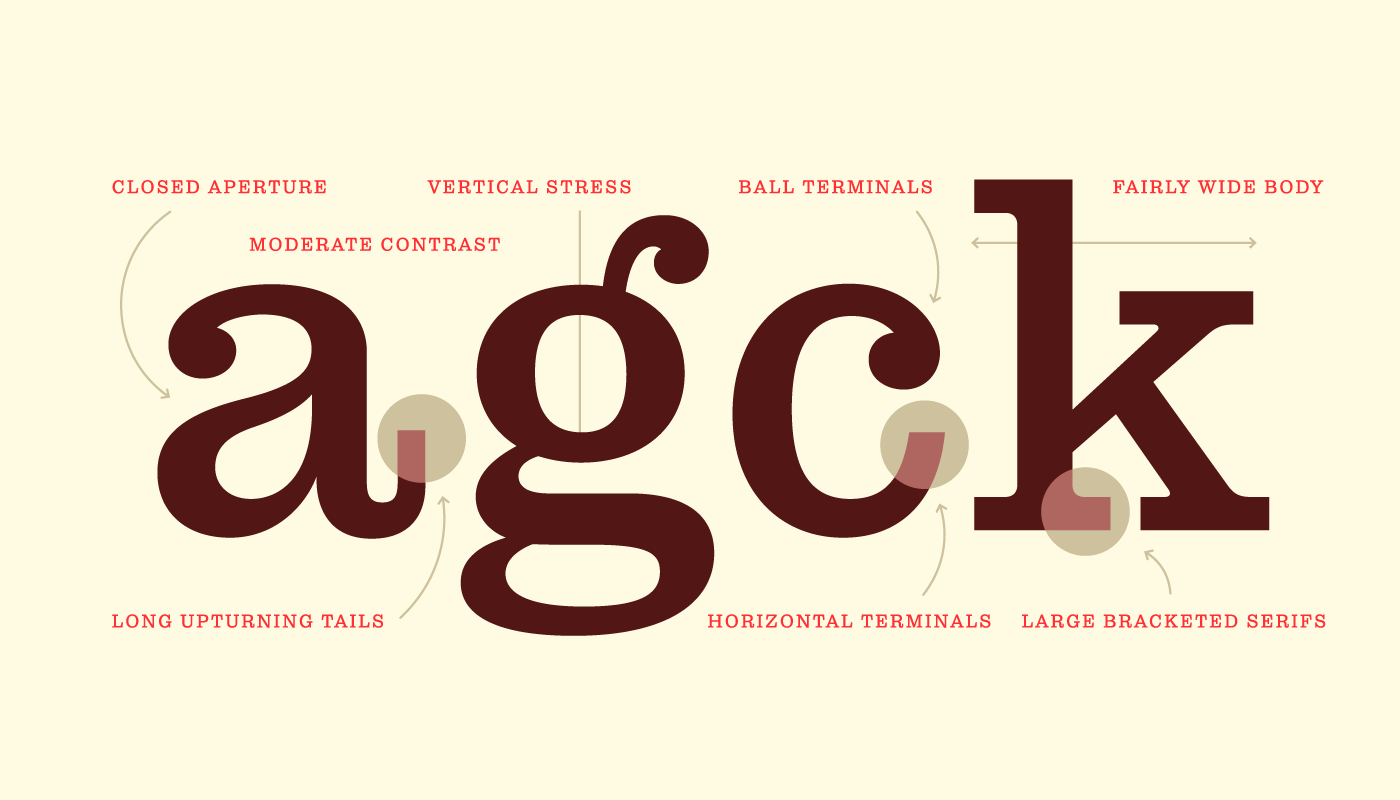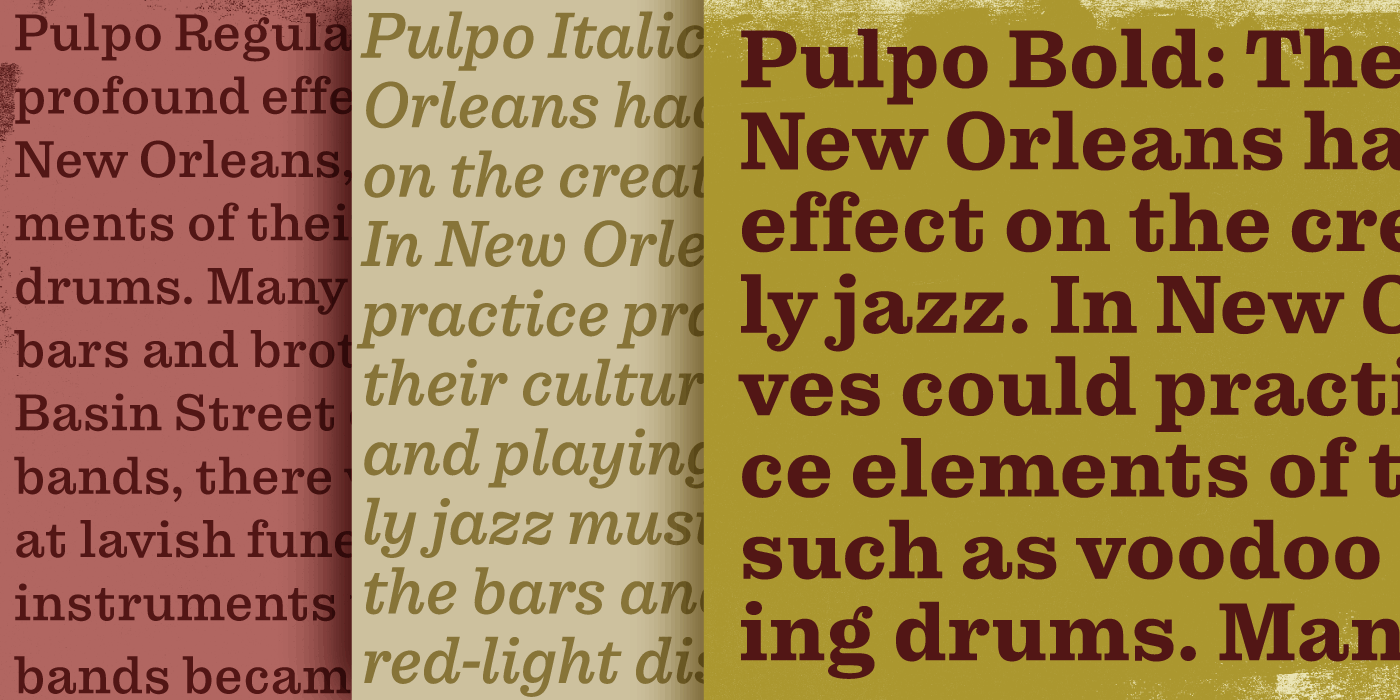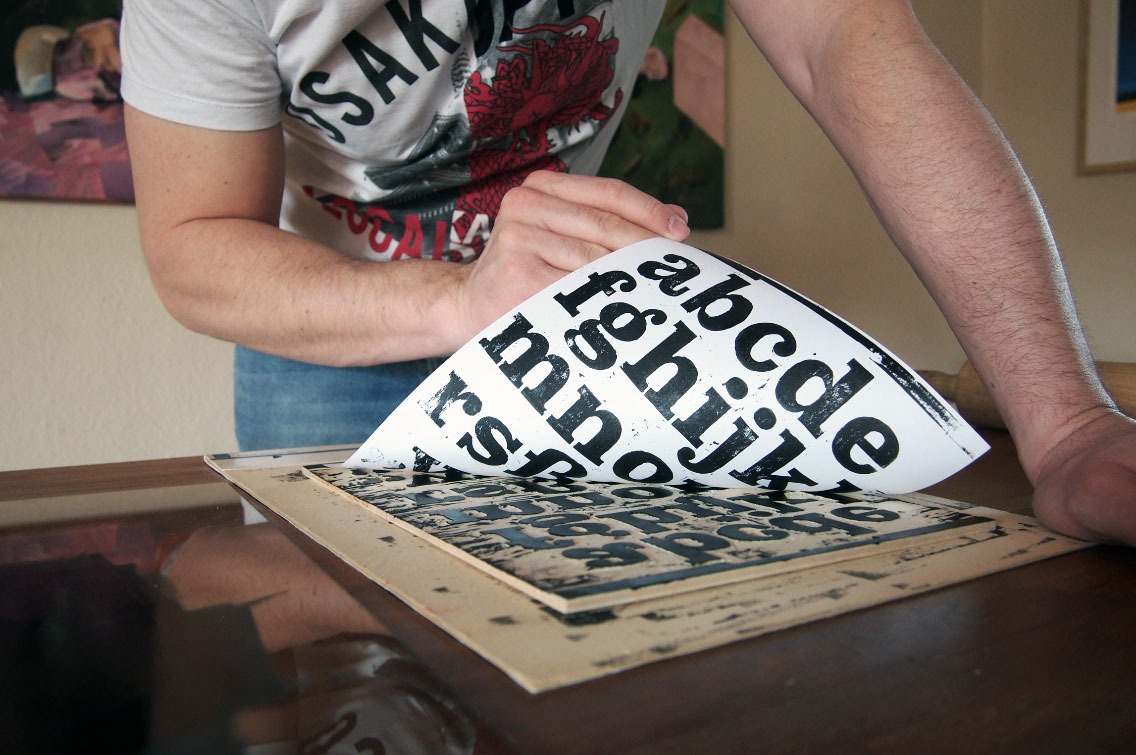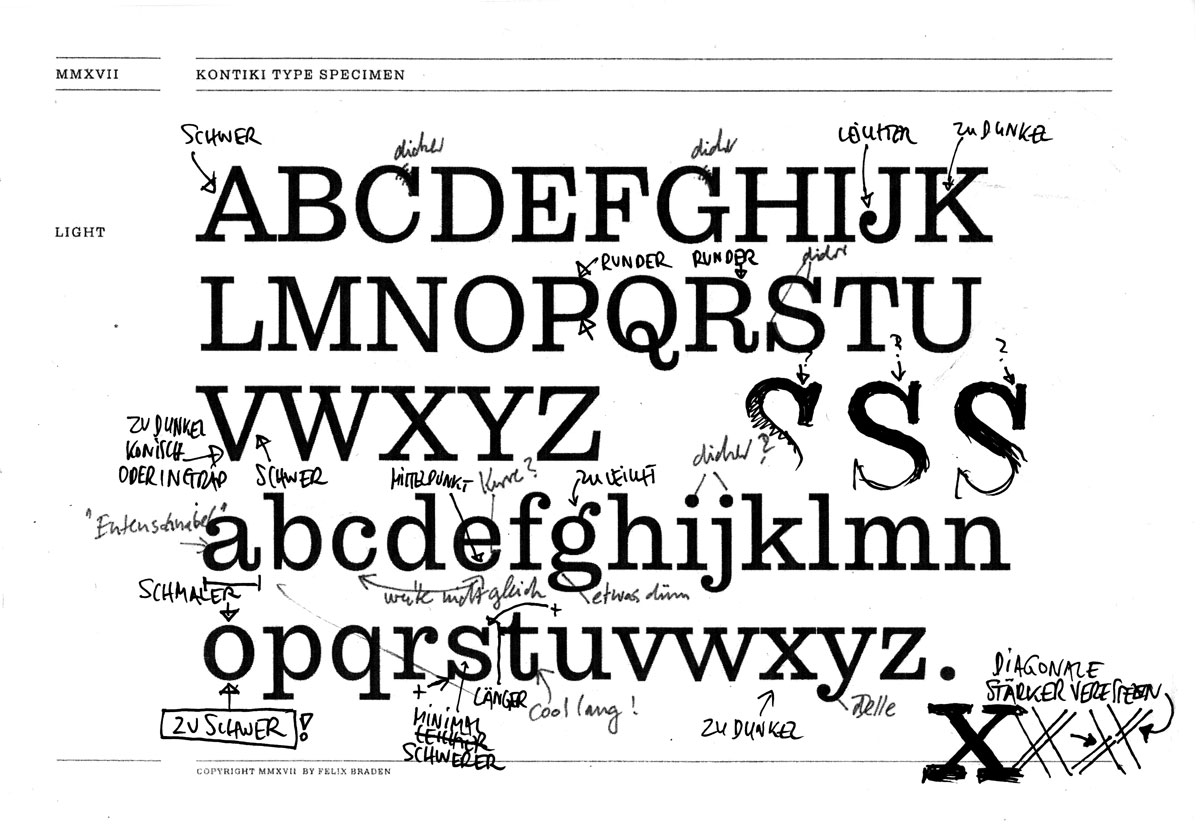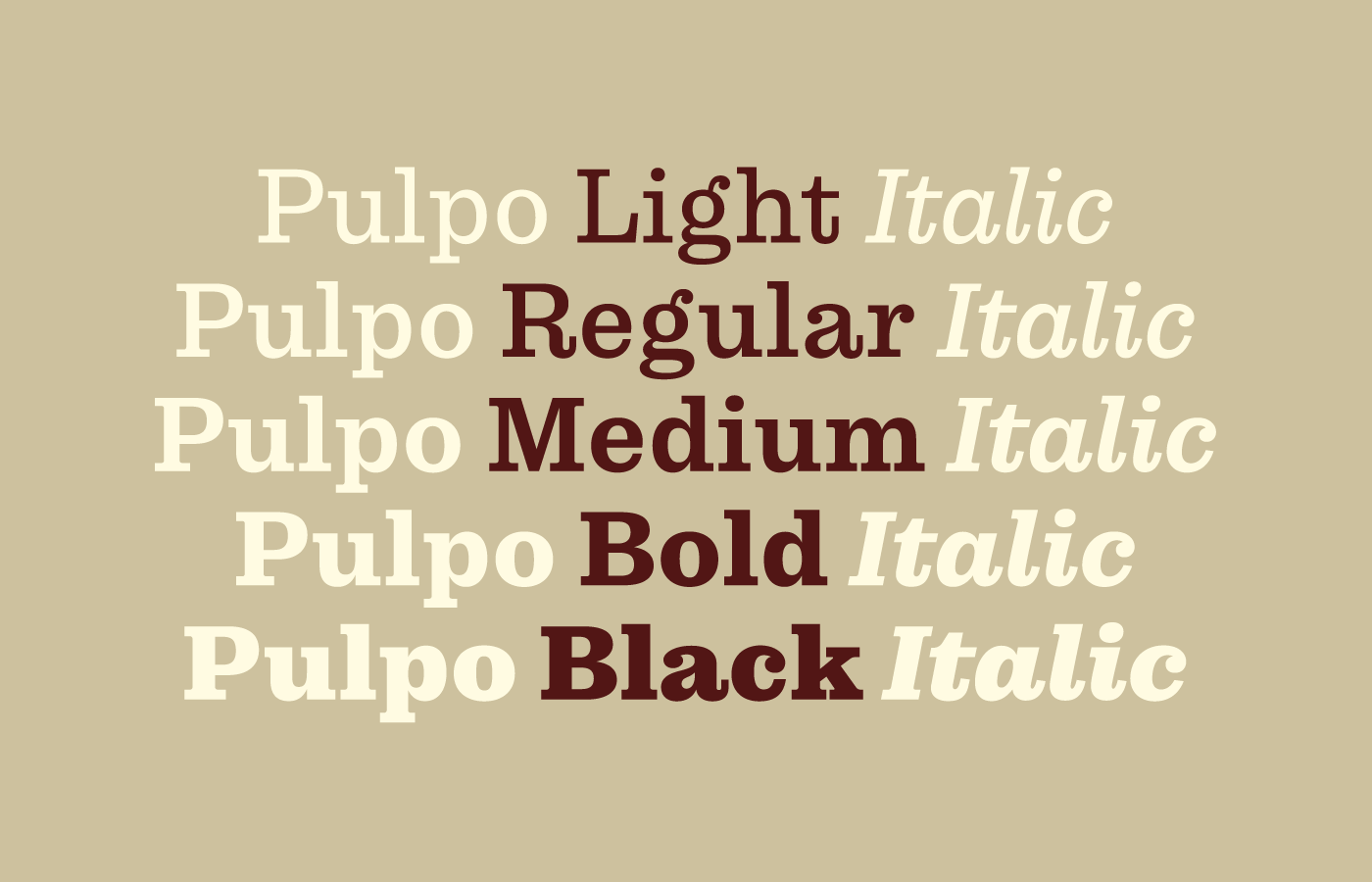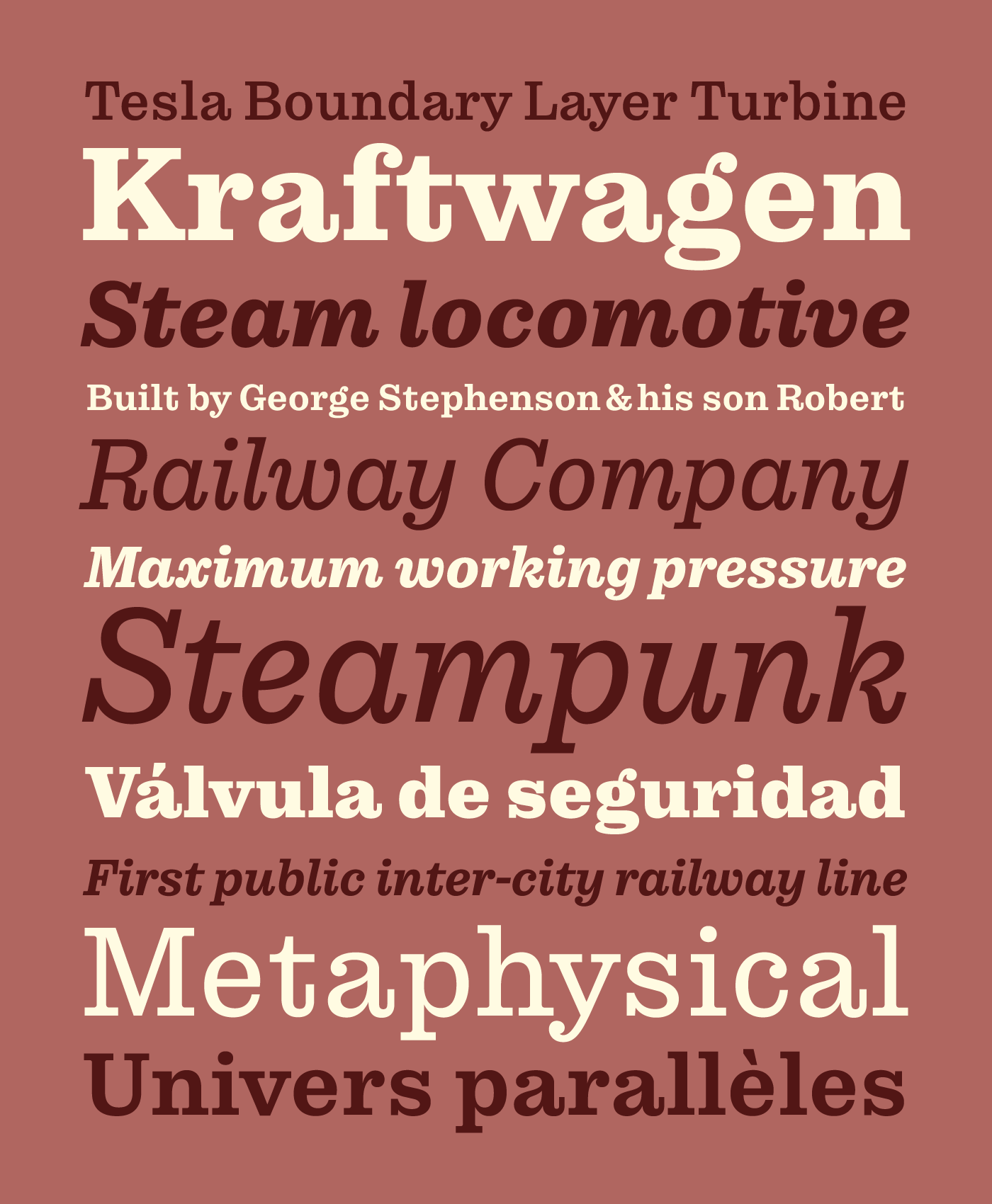
Pulpo – sympathische Clarendon für Lesetexte.
Design-Details von Pulpo: moderater Kontrast, vertikale Betonung, hohe, vertikale Abstriche
Neu aus dem Schriftlabor von Felix Braden (Floodfonts): Pulpo, eine gut lesbare Clarendon, mit dem Skelett von Century Schoolbook, in 5 Strichstärken plus echten Kursiven. Die Familie wurde von Felix auf Lesbarkeit getrimmt, was sich in vielen Designdetails niederschlägt. Längere Ober- und Unterlängen geben dem Text Luft zum Atmen und verbessern die Lesbarkeit von Fließtexten. Trotz typischer Slab-Serif-Stabilität im Design, wirken die Formen freundlich, wobei sich in vielen Details der handgemachte Charakter offenbart. Die Buchstaben wecken vertraute Erinnerungen und wirken ein wenig nostalgisch – wie aus der guten alten Zeit.
Die komplette Pulpo-Familie besteht aus 10 Schnitten, von Light bis Black (einschließlich Kursiven) und eignet sich vor allem für Editorial-Design, Werbung und Verpackung sowie für die Web- und App-Entwicklung. Ein massiver, stabiler Aufbau in Kombination mit einem geringen Strichstärkenkontrast, betont die horizontalen Elemente, und macht Pulpo zur perfekten Wahl für Lesetexte am Bildschirm und kleine Schriftgrößen auf Naturpapier.
Erstaunlich gut lesbar in Lesetexten, eine der Stärken der neuen Slab-Serif Pulpo
Jeder Schnitt enthält 489 Glyphen, Versal- und Mediävalziffern für Fließtext und Tabellensatz sowie mathematische Zeichen und gängige Währungszeichen. Um den Bedürfnissen der globalen Kommunikation gerecht zu werden bietet Pulpo eine umfangreiche Sprachunterstützung für alle west-, ost- und mitteleuropäischen Sprachen
Entstehungsprozess
Wie alles begann, beschreibt Felix Branden so: »2017 entschied ich mich, einen ganzen Satz Glyphen für einen manuellen Druckvorgang zu schneiden, der später als digitalisierte Schrift namens Kontiki auf Myfonts und als Pulpo Rust bei Adobe veröffentlicht wurde (vergl. Fontblog: Neue, lebendige Holzdruck-Schriftfamilie Kontiki). Als Basis suchte ich eine fette Schrift nach dem Clarendon-Muster, die ich schließlich selbst auf der Grundlage einer meiner Lieblingsschriftarten, Century Schoolbook, zeichnete. Die Skizzen dieser Clarendon gefielen mir dann so gut, dass ich mich dazu entschied, die Zahl der Schnitte auszubauen, um Kursiven zu erweitern und als eigenständige Familie mit dem Namen ›Pulpo‹ auf den Markt zu bringen.«
Das merkt man Pulpo an: erst in Holz geschnitten, dann Probedrucke angefertigt und danach digitalisiert
Die erste Clarendon übrigens wurde 1845 von der Fann Street Foundry veröffentlicht. Sie wurde von Robert Besley entworfen und von Benjamin Fox geschnitten. Als fette Erweiterung für die Textschriften dieser Zeit geplant (eine Alternative zu Kapitälchen oder Kursiven als Hervorhebung) gab es ursprünglich keine leichten bzw. Text-Schnitte der Clarendon, und natürlich auch keine Kursive. Im folgenden Jahrhundert wurde Clarendon zum Modell für eine Vielzahl von Schriften (z.B. der ›Clarendon‹ von Hermann Eidenbenz und Freeman Craws ›Craw Clarendon‹), die für den Bleisatz konzipiert, für den Fotosatz erweitert, und dann im beginnenden DTP-Zeitalter in den 90er Jahren digitalisiert wurden.
Century Schoolbook hat sich über Jahrzehnte von den Vorbildern der Scotch-Schriften über eine Zeitungsschrift (Century) zu einem Standard für schulische Texte in den Vereinigten Staaten entwickelt. Heute ist sie ein Synonym für gute Lesbarkeit geworden und für Felix Braden die Quintessenz der amerikanischen Schrift. Da die Proportionen der Zeichen perfekt ausbalanciert sind, und sie ein freundliches, angenehmes Gefühl auslösen, schien sie eine gute Inspirationsquelle für seine Clarendon zu sein.
Korrekturblatt von Pulpo: Nach dem Probedruck begann die Detailarbeit
»Um die aufrechten Schnitte von Pulpo zu erstellen, zeichnete ich über das Skelett der Century Schoolbook und entwarf eine Clarendon, indem ich den Kontrast reduzierte und typische Elemente wie lange Aufschwünge und waagerechte Abschlüsse hinzufügte. Einige Buchstaben, z.B. Das a oder das g mussten komplett überarbeitet werden, da sich die Buchstabenform von der Clarendon-Tradition unterscheidet.« erinnert sich Felix Braden an die Detailarbeit.
Für die Italics sei Jonathan Hoeflers ›Sentinel‹ eine gute Inspirationsquelle gewesen, wobei Felix den Weg ging, seine Italics eher statisch als geschrieben zu entwerfen. Seiner Meinung nach hätte es Aldo Novarese mit seiner ›Egizo Serie Corsiva‹ etwas »zu weit getrieben«, während die Kursiven von Matthew Carters ›New Century Schoolbook‹ genau seine Kragenweite seien. Wichtiges Konstruktionsmerkmal sei der obere linke Abschluss des n in Pulpo Italic, wie in den Aufrechten eine Serife und kein hakenförmiger Abstrich. Auf der anderen Seite wurden die waagerecht geschnittenen Aufschwünge abgemildert und an die vom Schreiben abgeleitete Form angepasst.
Die Pulpo-Familie im Überblick: 5 Strichstärken plus echte Kursive, inspiriert von Jonathan Hoeflers ›Sentinel‹
Da die Schrift auch in längeren Texten gut lesbar sein sollte, entschloss sich Felix dazu, einige dekorative Elemente zu entfernen, die bei kleinen Textgrößen nicht wirklich funktionieren. Insbesondere die nüchternen Ziffern unterscheiden sich von den historischen Clarendon-Beispielen.
Die neue, sympathische Pulpo: beste Lesbarkeit, zurückhaltende Kursive, raffinierte Details
Über Felix Braden
Felix lebt und arbeitet in Köln. Er hat an der Fachhochschule Trier Kommunikationsdesign bei Andreas Hogan studiert und mit Jens Gehlhaar bei Gaga Design gearbeitet. Er war eines der Gründungsmitglieder von Glashaus-Design, und arbeitet zur Zeit als Art Director bei MWK Cologne und als freischaffender Schriftgestalter. Im Jahr 2000 gründete er die Foundry Floodfonts und gestaltete viele kostenlose Schriften die über Adobe Typekit verfügbar sind (Moby, Bigfish, Hydrophilia, u.a.). Seine kommerziellen Schriften werden vertrieben vom Fontshop (FF Scuba), Floodfonts (Capri, Sadness, Grimoire), URW++ (Supernormale), Volcanotype (Bikini) und Ligature Inc (Tuna als Kooperation mit Alex Rütten). FF Scuba ist einer der Gewinner des Communication Arts Typography Annual 2013 und wurde in vielen Bestenlisten genannt darunter Typographica, Typefacts, Typecache und FontShop. Kontiki war für den German Design Award 2019 nominiert.